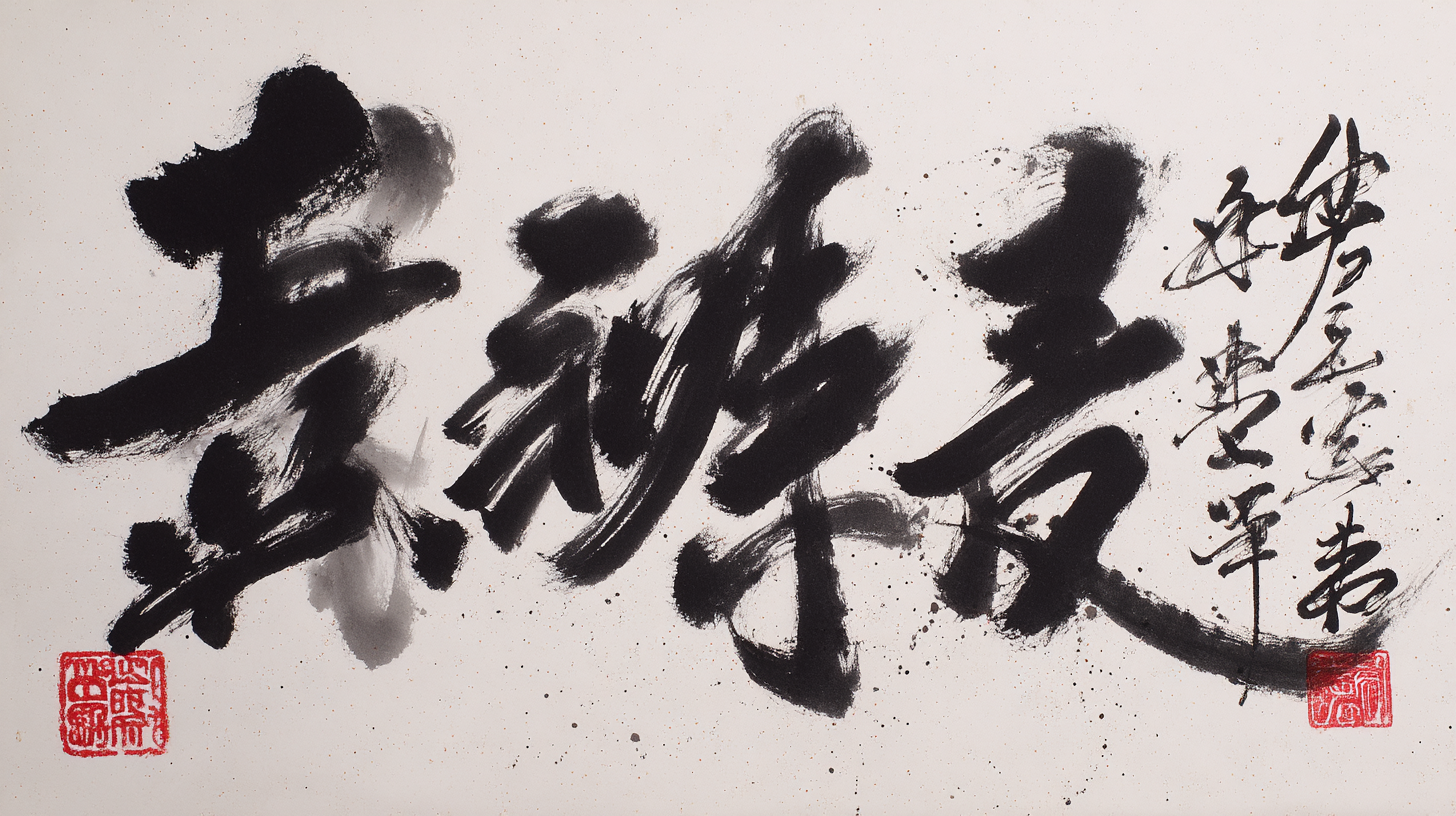
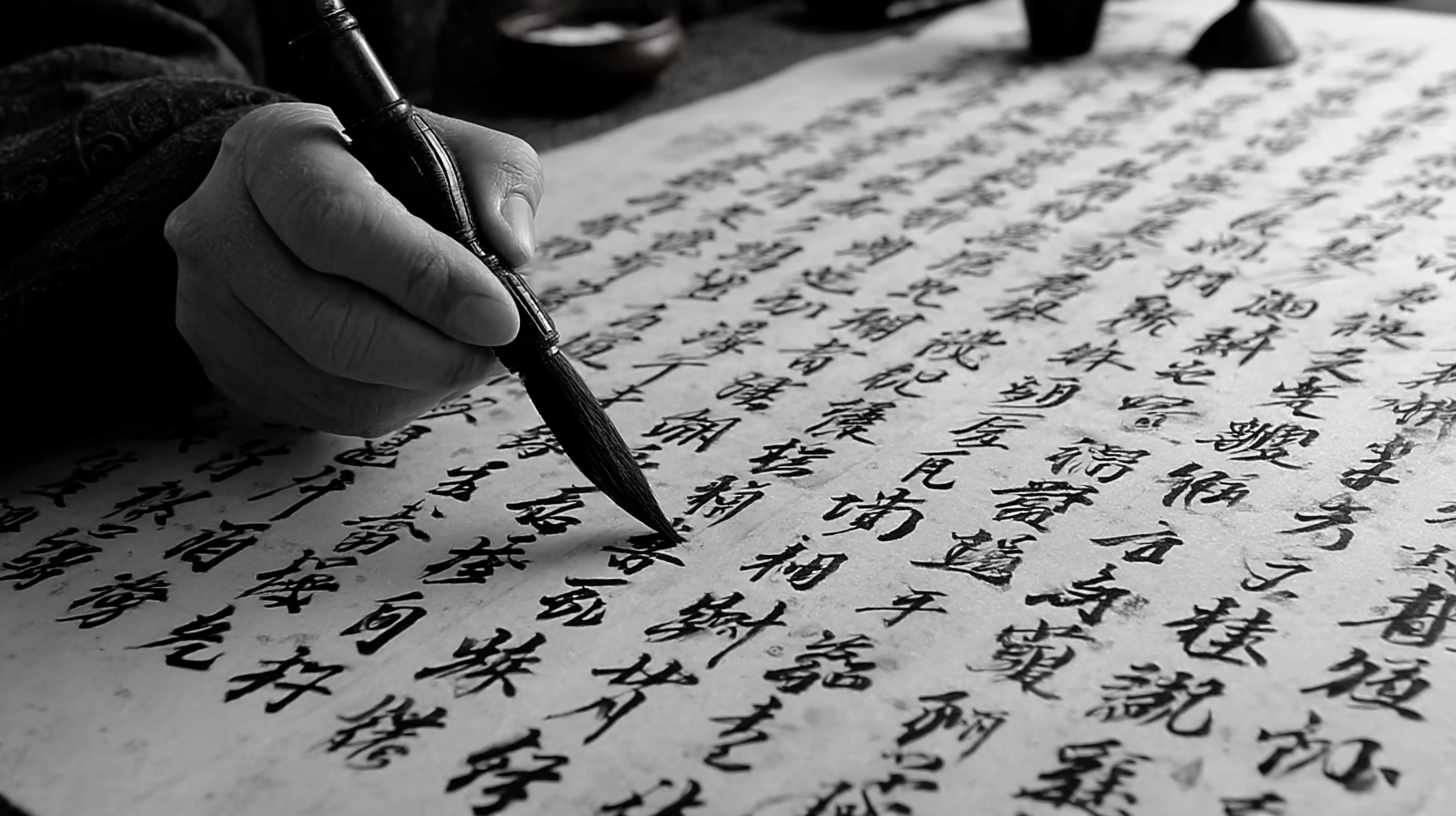
감성 가득한 캘리그라피 글귀 캘리그라피는 단순한 글쓰기에서 벗어나, 손글씨로 감정을 표현하는 예술이에요. 요즘은 인스타그램, 핸드메이드 카드, 브랜딩까지 다양한 분야에서 캘리그라피가 쓰이고 있어요. 예쁜 글귀 하나만으로도 사람의 마음을 사로잡을 수 있다는 점에서 정말 매력적인 작업이죠.
이번 글에서는 따뜻하고 감성적인 캘리그라피 문구 50개와 함께, 누구나 무료로 사용할 수 있는 한글 캘리그라피 폰트도 함께 소개할게요. 감성을 자극하는 글귀로 당신의 일상에 예술을 더해보세요 ✍
🖋 캘리그라피란 무엇인가요?
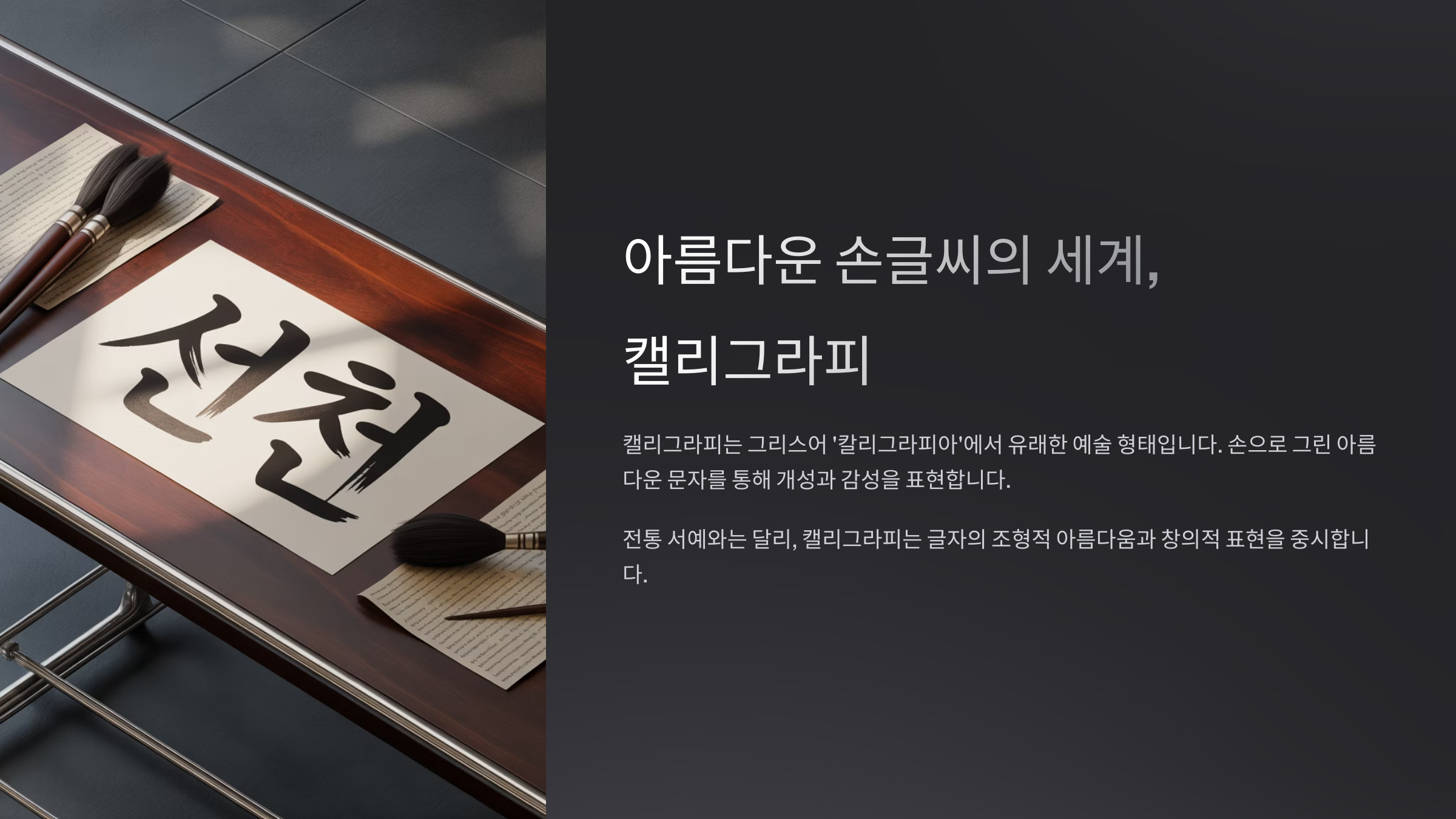
캘리그라피란 무엇인가요? 캘리그라피(Calligraphy)는 그리스어 'kallos(아름다움)'와 'graphein(쓰기)'에서 유래된 단어로, '아름답게 쓰다'라는 뜻이에요. 단순히 글자를 적는 행위를 넘어서, 감정과 철학을 담아낸 하나의 예술 형식으로 인정받고 있어요. 특히 한글 캘리그라피는 글자의 모양과 리듬감, 여백의 미를 살리는 데에 중점을 두고 있답니다.
현대에는 컴퓨터 타이포그래피가 발달했지만, 여전히 손으로 쓴 글씨는 사람의 감정과 온기를 그대로 전할 수 있다는 점에서 특별해요. 내가 생각했을 때 가장 감동적인 순간은 누군가 직접 써 준 캘리그라피 글귀를 선물받았을 때였어요. 기계로는 흉내 낼 수 없는 감성이 녹아 있었거든요.
한글 캘리그라피는 보통 붓펜, 만년필, 먹과 붓 등을 활용해서 자유롭게 쓰는 형식이에요. 여백의 균형, 글자 크기의 변화, 잉크의 농담이 섬세하게 조화를 이루며 보는 사람의 마음을 사로잡죠. 영어 캘리그라피와는 또 다른 매력이 있는 이유는, 한글의 곡선미와 조형미 덕분이랍니다.
요즘은 디지털 환경에서도 캘리그라피가 널리 활용돼요. 특히 로고 디자인, 책 표지, 브랜딩, 광고 이미지, SNS 콘텐츠에 활용되면서 상업적인 가치도 높아지고 있어요. 감정이 전해지는 글자 하나로 브랜드의 분위기를 바꾸기도 하죠.
캘리그라피는 명확한 정답이 없는 예술이에요. 어떤 사람은 간결한 획에서 감동을 느끼고, 또 어떤 사람은 화려한 곡선에서 따뜻함을 받아들이죠. 정형화되지 않은 자유로운 글씨이기에 누구나 시도해볼 수 있다는 점도 캘리그라피의 큰 매력이에요.
초보자도 쉽게 배울 수 있는 점도 캘리그라피의 장점이에요. 처음엔 따라 쓰는 것만으로도 좋고, 익숙해지면 나만의 스타일을 만들어갈 수 있어요. 무엇보다 중요한 건 꾸준히 쓰고, 느끼고, 자신만의 감성을 녹여내는 거랍니다.
이처럼 캘리그라피는 단순한 글씨체가 아니라, 자신의 내면을 글씨로 표현하는 도구예요. 한 글자 한 글자에 마음을 담고, 그 감정을 누군가에게 전할 수 있다는 건 참 멋진 일이죠. 요즘처럼 디지털에 익숙한 세상일수록, 손글씨의 따뜻함은 더욱 특별하게 느껴져요.
🖌 캘리그라피 도구 비교표
도구 장점 단점 추천 대상 붓펜 손쉬운 조작, 초보자용 붓의 느낌은 다소 부족 입문자 붓과 먹 전통 느낌, 감성 극대화 세팅 시간, 번짐 중급 이상 만년필 날렵한 선 표현 가능 먹 느낌은 부족 모던한 느낌 선호자 디지털 태블릿 수정 간편, 다양한 스타일 감성 전달은 다소 제한 디자이너, 인플루언서 자신에게 맞는 도구를 고르면, 캘리그라피의 매력을 더 깊이 느낄 수 있어요. 간단한 붓펜부터 시작해보고, 점점 다양한 재료를 사용하면서 글씨와 감성을 함께 성장시켜보세요 🎨
🎨 캘리그라피 스타일 종류
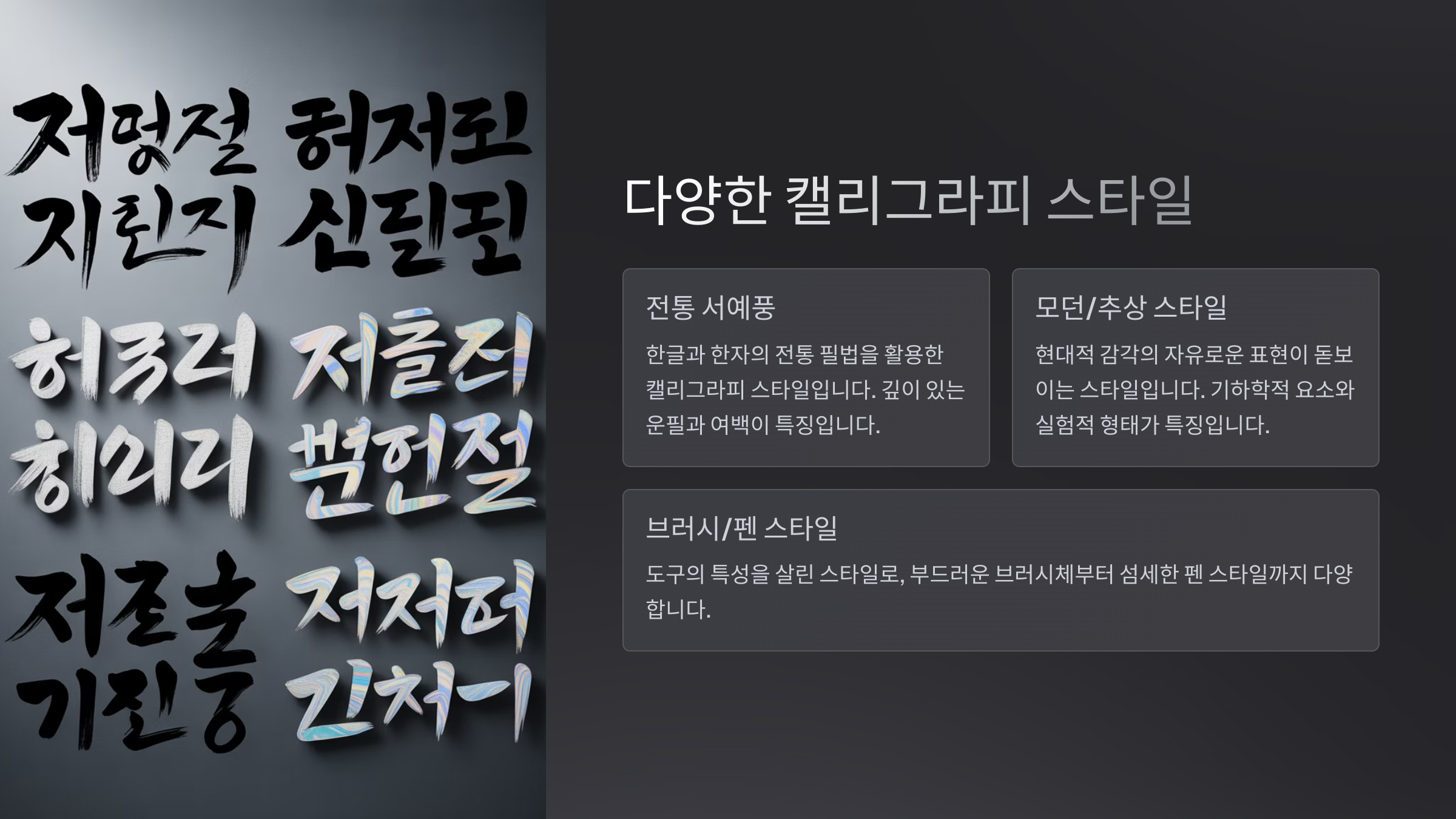
캘리그라피 스타일 종류 캘리그라피는 한 가지 형태로 정해져 있는 게 아니에요. 표현하는 사람의 감성과 의도에 따라 정말 다양한 스타일이 존재하죠. 단아하고 조용한 느낌부터, 강렬하고 역동적인 붓터치까지 각각의 개성 있는 매력이 있답니다. 글씨 하나만 봐도 그 사람의 감정이 느껴질 정도예요.
대표적인 스타일로는 정형 캘리그라피, 자유형 캘리그라피, 모던 캘리그라피, 일러스트 캘리그라피 등이 있어요. 정형은 말 그대로 전통적인 방식에 가까운 스타일이에요. 붓글씨 수업에서 자주 접할 수 있고, 단정하고 안정감 있는 형태로 표현돼요.
반대로 자유형은 형태나 구조에 얽매이지 않고 본인의 감정을 그대로 쏟아내는 스타일이에요. 감정이 격해질수록 선이 거칠어지고, 글자의 배열이 비대칭으로 흐르는 경우도 많죠. 이건 오히려 완벽함보다는 불완전함 속의 감정을 표현하는 데 초점이 맞춰져 있어요.
모던 캘리그라피는 현대적 감각이 가미된 스타일이에요. 굵기 조절이나 구성이 세련되고 트렌디한 느낌을 줘요. SNS나 카페 메뉴판, 제품 패키지 디자인 등에서도 많이 볼 수 있어요. 정돈된 듯하면서도 감성을 잃지 않아 많은 사랑을 받고 있답니다.
또한 일러스트 캘리그라피는 텍스트에 그림 요소를 결합해 표현한 형태예요. 예를 들어 “봄”이라는 단어에 꽃잎이나 나뭇잎 모양을 곁들이는 식이죠. 이런 방식은 감성적인 메시지를 더 강하게 전달할 수 있어서 카드나 포스터 제작에 많이 활용돼요.
이외에도 ‘미니멀 캘리그라피’, ‘팝 아트 캘리그라피’, ‘그래피티 스타일’까지 다양하게 존재해요. 각각이 가진 특징은 다르지만, 공통점은 글씨에 감성을 담아낸다는 거예요. 같은 단어도 어떤 스타일로 표현하느냐에 따라 완전히 다른 분위기를 만들 수 있어요.
처음엔 어떤 스타일이 나에게 맞는지 알기 어려울 수 있어요. 그래서 다양한 캘리그라피 예시를 많이 보고, 실제로 따라 써보는 게 좋아요. 감정의 흐름을 그대로 담아내다 보면 어느새 나만의 스타일이 만들어질 거예요 ✍
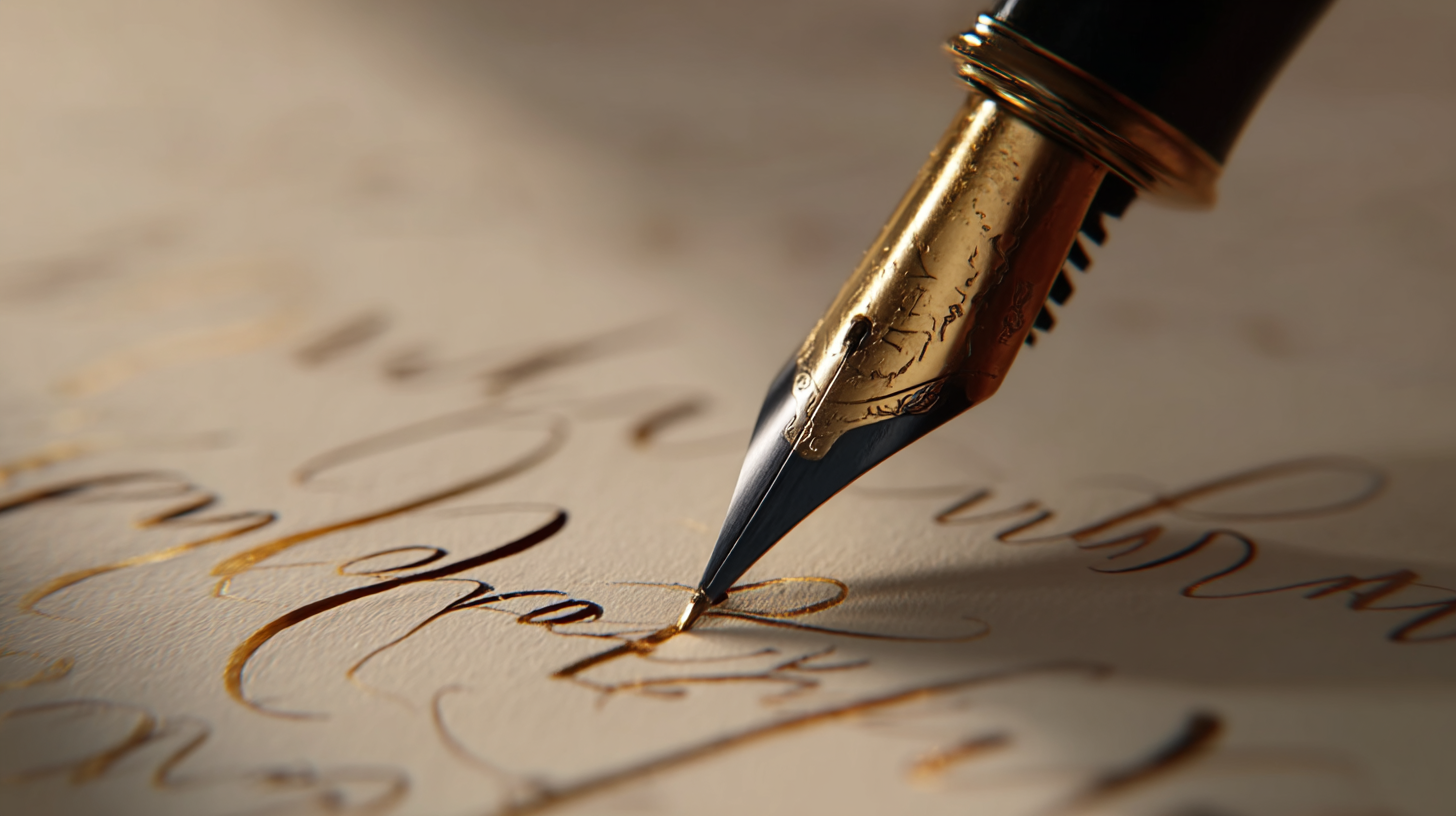
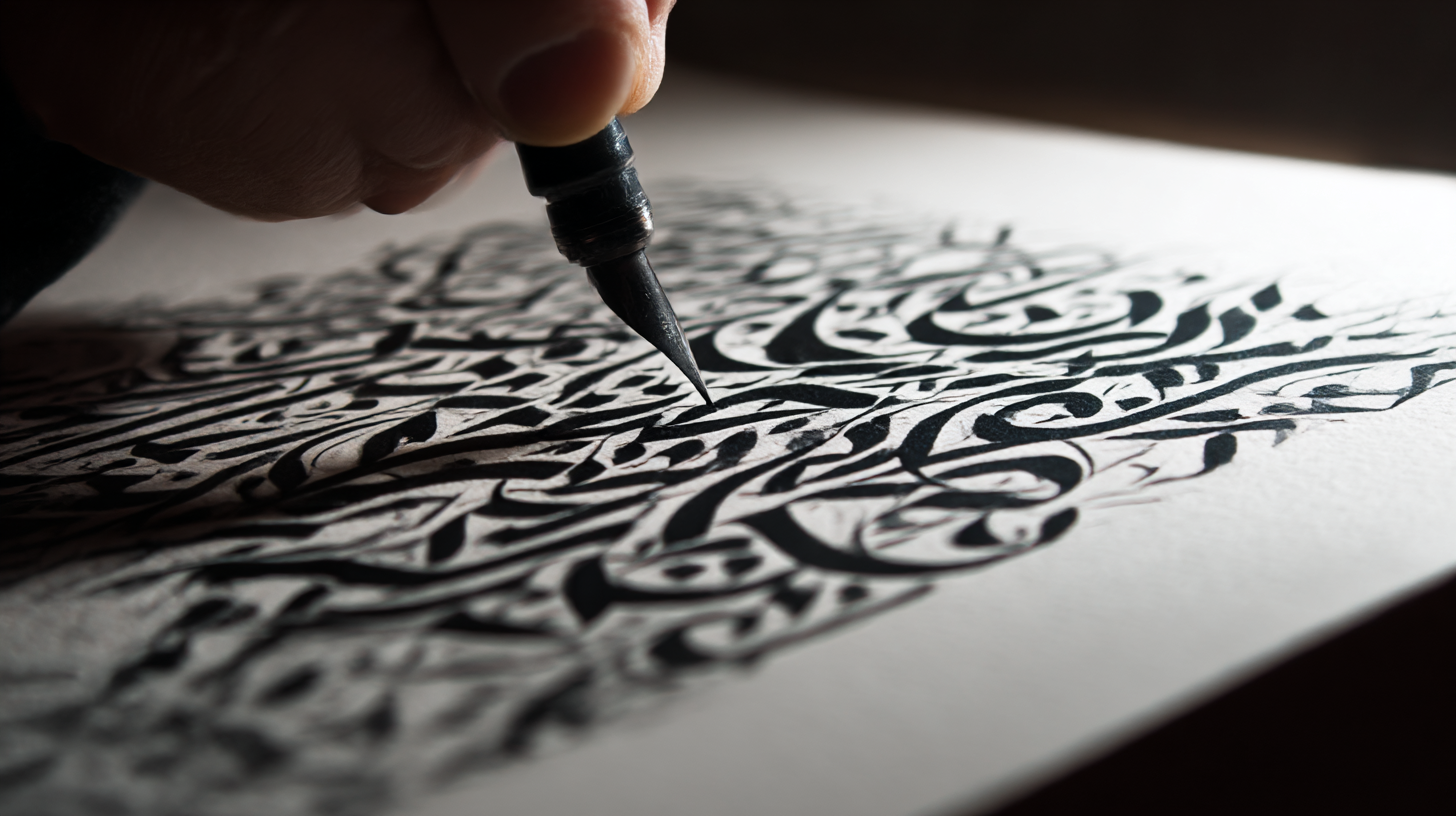
캘리그라피 스타일 종류 ✒ 캘리그라피 스타일 비교표
스타일 특징 주 사용처 난이도 정형 단정, 고전미 강조 공모전, 수묵화 ★★★☆☆ 자유형 감정 표현 중심 명언, 에세이 ★★☆☆☆ 모던 세련된 구성 디자인, 패키지 ★★★☆☆ 일러스트형 그림과의 조합 포스터, 엽서 ★★★☆☆ 어떤 스타일이든 상관없어요. 가장 중요한 건 '자신의 감정'을 글자에 담는 거예요. 그 자체로 이미 멋진 작품이니까요 ✨
📝 감성적인 캘리그라피 글귀 50선
감성적인 캘리그라피 글귀 50선 캘리그라피의 핵심은 ‘글귀’에 담긴 감성이에요. 때론 짧은 한 줄이 누군가의 하루를 위로하기도 하고, 삶을 돌아보게 만들기도 하죠. 그래서 오늘은 누구나 쉽게 따라 쓰고 마음을 담아 전달할 수 있는 캘리그라피 문구 50개를 소개할게요. 이 글귀들은 일상 속 소소한 위로부터 시작해 사랑, 도전, 행복, 계절의 감성까지 모두 아우르고 있어요 🍃
아래 문구들은 손글씨로 표현하기 좋게 구성돼 있으며, 짧고 간결하지만 울림이 있는 메시지로 구성했어요. 직접 써보면 정말 감동적이고, 내 글씨에 생명력이 깃드는 느낌이 든답니다. 엽서, 탁상달력, 다이어리, SNS 이미지 등에 활용하면 분위기가 확 달라져요.
자, 이제 50개의 감성적인 캘리그라피 문구를 카테고리별로 나누어 살펴볼게요. 각 문구는 다양한 분위기를 연출할 수 있도록 의도적으로 스타일을 달리 구성했어요. 천천히 한 줄 한 줄 써보면서 자신만의 필체를 녹여보세요. 이 문구들이 누군가에겐 큰 힘이 되어줄지도 몰라요 😊
🍀 힐링과 위로의 글귀
1. 오늘도 충분히 잘했어요
2. 괜찮아, 다 잘 될 거야
3. 지금도 충분히 예뻐요
4. 쉼도 용기예요
5. 울어도 괜찮아요
6. 느려도 괜찮아, 내 속도로 가는 거야
7. 나에게 더 잘해줘야 해요
8. 아프면, 아프다고 말해도 돼요
9. 조금 쉬어가도 괜찮아
10. 매일이 새로워질 거야
❤ 사랑과 감성
11. 사랑은 말보다 행동이에요
12. 당신이 있어서 참 다행이에요
13. 사랑은 언제나 옳아요
14. 내 마음이 닿기를
15. 우리는 서로의 봄이에요
16. 당신의 미소가 내 하루를 밝혀요
17. 마음은 눈빛보다 먼저 전해져요
18. 조용한 사랑이 더 깊은 법이죠
19. 당신은 오늘도 충분히 예뻐요
20. 고마워요, 내 곁에 있어줘서
💖 글귀 구성 팁 요약표
분류 글귀 스타일 추천 분위기 위로 짧고 부드러운 어조 다이어리, 힐링 노트 사랑 감정 중심, 따뜻한 표현 러브레터, 포토북 🌈 희망과 긍정의 말들
21. 내일은 더 좋은 날이 될 거예요
22. 믿는 만큼 이루어진다
23. 포기하지 마요, 지금이 가장 가까워요
24. 오늘도 무언가 배우는 하루
25. 작지만 확실한 행복을 찾아서
26. 나아가는 중이야, 멋지게
27. 세상엔 아직 예쁜 것들이 많아요
28. 내 걸음은 나만의 리듬으로
29. 조금씩, 천천히, 하지만 확실하게
30. 당신이 생각보다 훨씬 대단해요
📅 계절과 일상
31. 봄은 또 오니까요
32. 햇살 좋은 날, 당신이 생각나요
33. 계절이 바뀌듯, 우리 마음도 자라요
34. 여름엔 마음까지 반짝이길
35. 가을엔 마음이 따뜻해져요
36. 겨울은 그리움을 품고 있어요
37. 하루하루가 선물이에요
38. 찰나의 순간을 사랑하자
39. 지금 이대로도 충분히 좋아요
40. 마음에 담는 풍경들
🌟 자기 다짐과 도전
41. 나를 믿는 연습을 해요
42. 다시 시작해도 괜찮아
43. 오늘은 어제보다 한 뼘 성장
44. 노력은 배신하지 않아요
45. 실수는 과정일 뿐이에요
46. 나를 응원해요, 내가 제일 오래된 친구니까요
47. 도전은 나를 향한 선물
48. 무너지지 말고, 흔들리지 말고
49. 끝까지 간 사람만이 본다
50. 매일이 도전이고, 나는 그 주인공
이 문구들을 따라 써보는 것만으로도 나만의 감성 캘리그라피가 완성돼요. 마음에 드는 글귀를 골라 연습장이나 카드에 직접 써보세요. 사람의 손끝에서 나오는 글씨는 늘 특별한 힘이 있어요 ✨
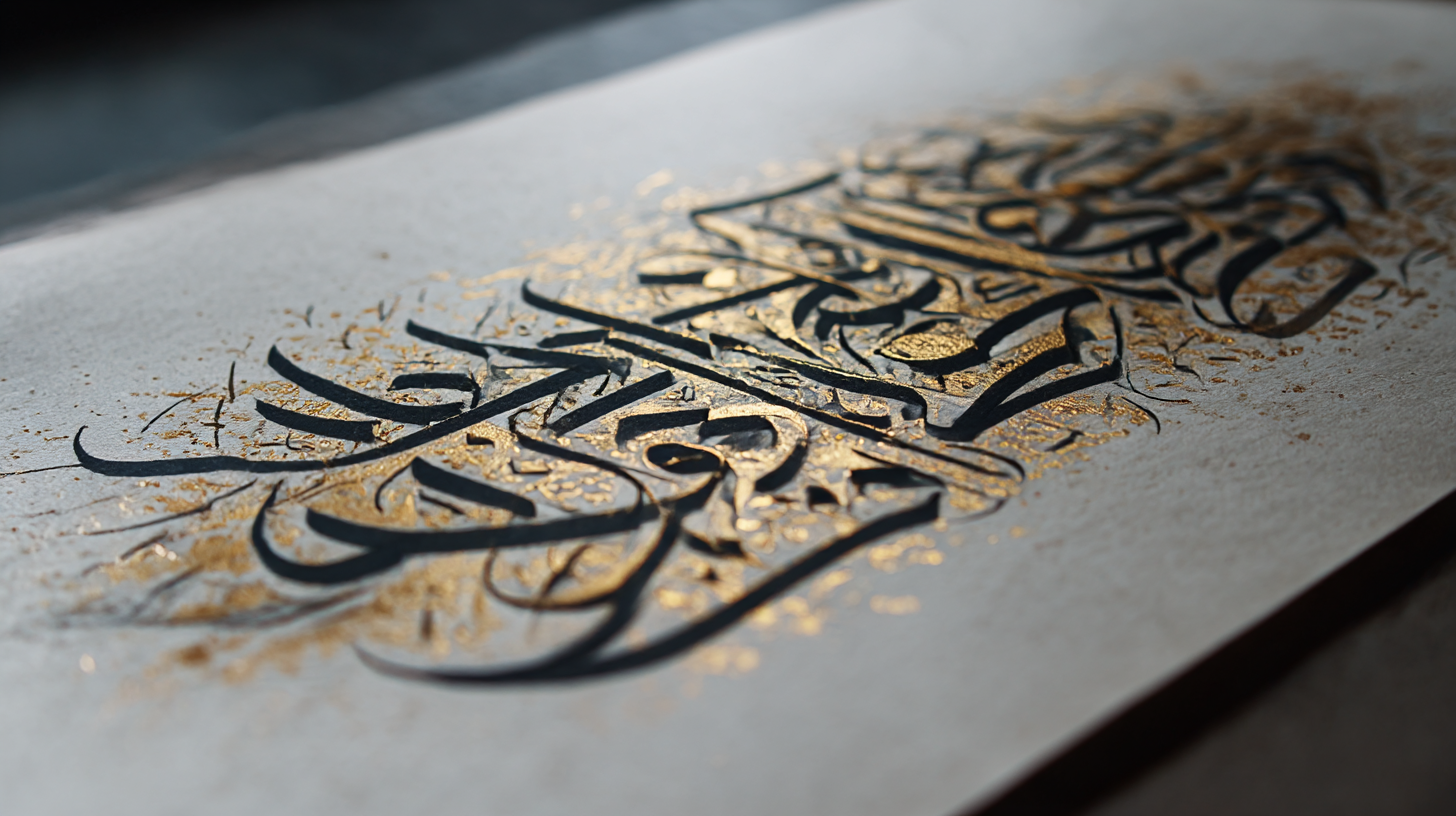
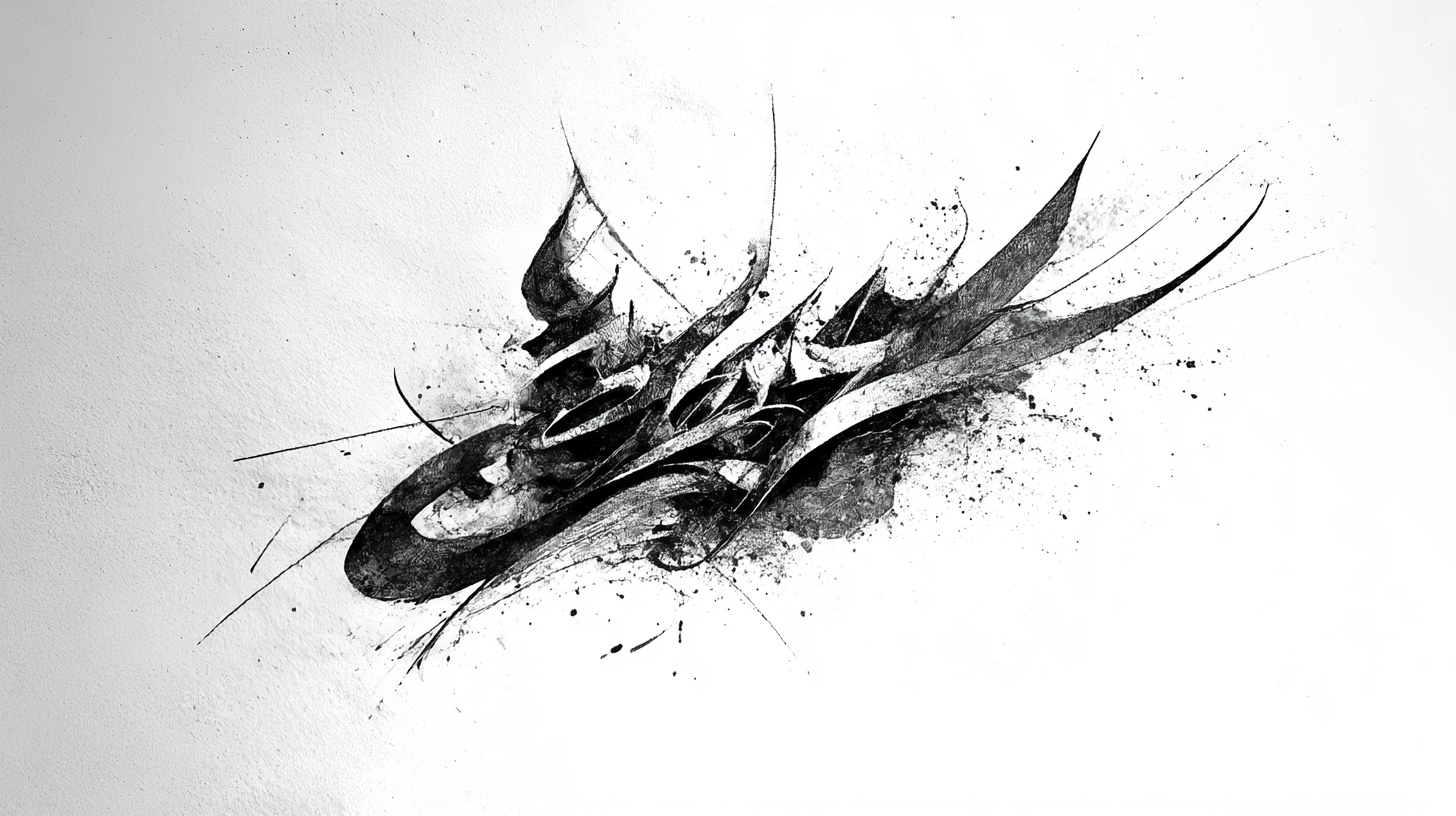
감성적인 캘리그라피 글귀 50선 🔤 무료로 사용할 수 있는 폰트
A3. Procreate, Adobe Fresco, ibisPaint 등이 좋아요. 모두 레이어 기능과 필압 감지가 잘 되어 있어요.
Q4. 감성적인 글귀는 어디서 참고하나요?
A4. 시집, 에세이, SNS 명언 페이지, 감성 블로그에서 찾을 수 있어요. 자신이 느낀 감정을 짧게 써보는 것도 좋아요.
Q5. 내 글씨가 예쁘지 않아도 괜찮을까요?
A5. 물론이에요! 예쁘지 않아도 감정이 담긴 글씨가 가장 아름다워요. 나만의 개성이 훨씬 중요하답니다.
Q6. 캘리그라피로 수익을 낼 수 있을까요?
A6. 충분히 가능해요. 굿즈 제작, 엽서 판매, SNS 콘텐츠 제작, 클래스 운영 등으로 수익화하는 분들이 많아요.
Q7. 손글씨 연습은 얼마나 자주 해야 하나요?
A7. 하루 10분이라도 꾸준히 연습하면 실력이 금방 늘어요. 짧은 명언 하나씩 써보는 연습이 제일 좋아요.
Q8. 상업적 활용 시 꼭 확인할 점이 있나요?